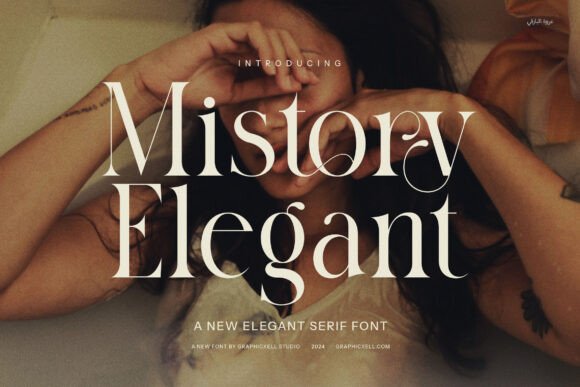
Mistory Elegant Font
Mistory Elegant Fontのような高品質の素材をお探しの場合、このプレミアムパッケージはクリエイティブなプロジェクトに素晴らしい選択です。
POD(オンデマンド印刷)製品、結婚式の招待状、またはソーシャルメディアのグラフィックを作成している場合でも、Mistory Elegant Fontは理想的です。